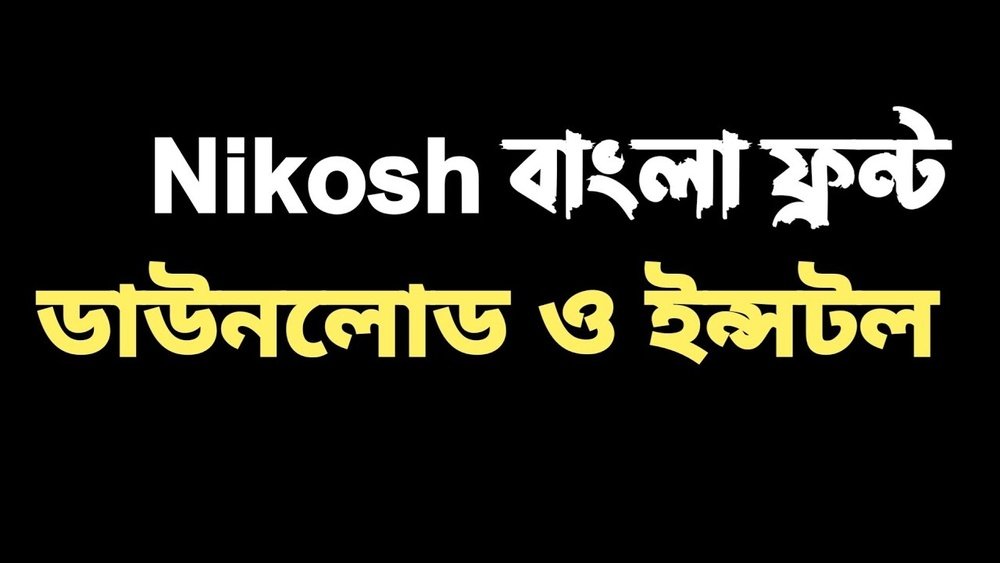
Nikosh Bangla Font Download: দ্রুত ও সহজ ফন্ট সংগ্রহ করুন
আপনি কি এমন একটি বাংলা ফন্ট খুঁজছেন যা আপনার লেখাকে আরও সুন্দর এবং পেশাদার দেখাবে? তাহলে Nikosh Bangla Font Download আপনার জন্য একদম সঠিক পছন্দ। এই ফন্টটি ব্যবহার করলে আপনার ডিজাইন, ব্লগ, অথবা যেকোনো বাংলা লেখার কাজ হবে আরও আকর্ষণীয় এবং পাঠযোগ্য। আপনি যদি দ্রুত, সহজে এবং বিনামূল্যে Nikosh Bangla ফন্ট ডাউনলোড করতে চান, তাহলে এই আর্টিকেলটি আপনার জন্য। এখানে আমরা আপনাকে দেখাবো কিভাবে Nikosh Bangla ফন্ট সহজে ডাউনলোড করবেন এবং সেটিকে আপনার কম্পিউটার বা মোবাইলে ব্যবহার করবেন। আপনার লেখার দক্ষতা বাড়াতে এবং চোখে পড়ার মতো ডিজাইন করতে এখনই পড়া শুরু করুন!
Nikosh Bangla Font পরিচিতি ও এর প্রয়োজনীয়তা
Nikosh Bangla Font হলো একটি জনপ্রিয় বাংলা ফন্ট, যা ডিজিটাল লেখার জন্য বিশেষভাবে তৈরি। এটি বাংলা ভাষার স্বচ্ছন্দ এবং সঠিক উপস্থাপনার জন্য ব্যবহৃত হয়। ডিজিটাল মিডিয়ায় বাংলা লেখার মান বাড়াতে Nikosh Bangla Font অপরিহার্য।
বাংলা ভাষার উন্নত ডিজিটাল প্রচারের ক্ষেত্রে ফন্টের ভূমিকা খুবই গুরুত্বপূর্ণ। Nikosh Bangla Font এর মাধ্যমে লেখাগুলো আরও পাঠযোগ্য ও আকর্ষণীয় হয়। ফলে, বাংলা ভাষার ডিজিটাল ব্যবহার সহজ ও ফলপ্রসূ হয়।
Nikosh Bangla Font কি এবং এর উদ্দেশ্য
Nikosh Bangla Font একটি ডিজিটাল বাংলা ফন্ট, যা বাংলা লিপির সঠিক রূপে লেখার জন্য তৈরি। এর মূল উদ্দেশ্য হলো বাংলা ভাষার জন্য একটি সুন্দর, পড়তে সহজ এবং কম্পিউটার বা মোবাইলের সাথে সামঞ্জস্যপূর্ণ ফন্ট সরবরাহ করা।
ফন্টটি বাংলা ভাষার বিভিন্ন লেখায় ব্যবহার করা যায়, যেমন:
• ওয়েবসাইট ডিজাইন
• ডকুমেন্ট ও রিপোর্ট
• গ্রাফিক ডিজাইন
• শিক্ষা ও প্রকাশনা
এটি বাংলা ভাষাকে ডিজিটাল মাধ্যমে আরও শক্তিশালী করে তোলে।
বাংলা ডিজিটাল লেখার ক্ষেত্রে Nikosh Bangla Font এর গুরুত্ব
ডিজিটাল বাংলায় ফন্টের মান ও সঠিকতা লেখার গুণগত মান নির্ধারণ করে। Nikosh Bangla Font এর কিছু গুরুত্বপূর্ণ বৈশিষ্ট্য:
বৈশিষ্ট্য বর্ণনা
স্বচ্ছতা পড়তে সহজ, চোখে আরামদায়ক
সামঞ্জস্য বিভিন্ন প্ল্যাটফর্ম ও ডিভাইসে কাজ করে
বহুমাত্রিকতা বিভিন্ন ফরম্যাটে ব্যবহার উপযোগী
বাংলা অক্ষর সঠিকতা বাংলা লেখার সব অক্ষর সঠিকভাবে প্রদর্শন করে
এই ফন্ট ব্যবহার করলে ডিজিটাল বাংলা লেখার মান বৃদ্ধি পায়। বাংলা ভাষার প্রতি শ্রদ্ধাশীল ও পেশাদার পরিবেশ তৈরি হয়।
Nikosh Bangla Font Download: দ্রুত ও সহজ ফন্ট সংগ্রহ করুন
Nikosh Bangla Font এর বিশেষ বৈশিষ্ট্য
Nikosh Bangla Font বাংলা লেখার জন্য একটি জনপ্রিয় ফন্ট। এটি ব্যবহার করলে লেখা হয়ে ওঠে আরও সুন্দর ও পরিষ্কার। ফন্টটি বাংলা ভাষার স্বাতন্ত্র্য বজায় রেখে ডিজাইন করা হয়েছে। তাই এটি যেকোনো বাংলা লেখায় ব্যবহার উপযোগী।
এই ফন্টের কিছু বিশেষ বৈশিষ্ট্য রয়েছে, যা ব্যবহারকারীদের জন্য সুবিধাজনক। নিচে এই বৈশিষ্ট্যগুলো বিস্তারিত আলোচনা করা হলো।
বাংলা লেখায় স্বচ্ছতা ও পড়ার সুবিধা
Nikosh Bangla Font ব্যবহার করলে বাংলা লেখা হয় স্পষ্ট ও পরিষ্কার। অক্ষরগুলো সুন্দরভাবে সাজানো থাকে।
• বাংলা হরফের প্রতিটি ডিটেইল স্পষ্টভাবে দেখা যায়।
• লেখা পড়তে সহজ হয়, চোখে আরাম দেয়।
• বিভিন্ন ডিজিটাল মাধ্যমেও সুন্দরভাবে প্রদর্শিত হয়।
এটি বিশেষ করে দীর্ঘ লেখার জন্য উপযোগী, কারণ এতে চোখে ক্লান্তি কম হয়।